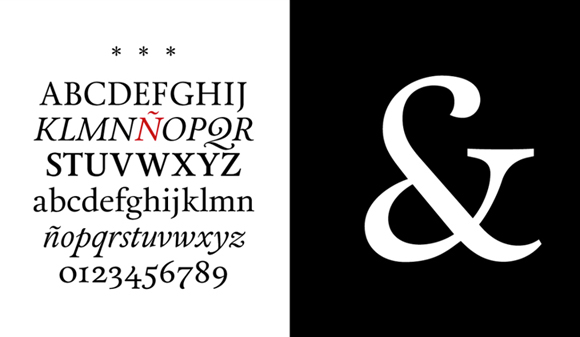
Desde Gijón en Asturias el estudio de diseño atipo™ no contentos con sorprendernos con sus excelentes trabajos gráficos, esta vez lo hacen con una tipografía de creación propia llamada Calendas de excelente calidad, según bien cuentan, tiene un aire clásico, gran legibilidad y elegancia, esta diseñada para trabajar en tamaños pequeños y su personalidad viene marcada por sus remates caligráficos. Ademas cuenta con 3 estilos, la Regular (con auténticas versalitas, ligaduras, juegos de numerales y otras sorpresas OpenType) una cursiva y la negrita. Una buena familia tipográfica que puede jugar un buen papel en usos editoriales.